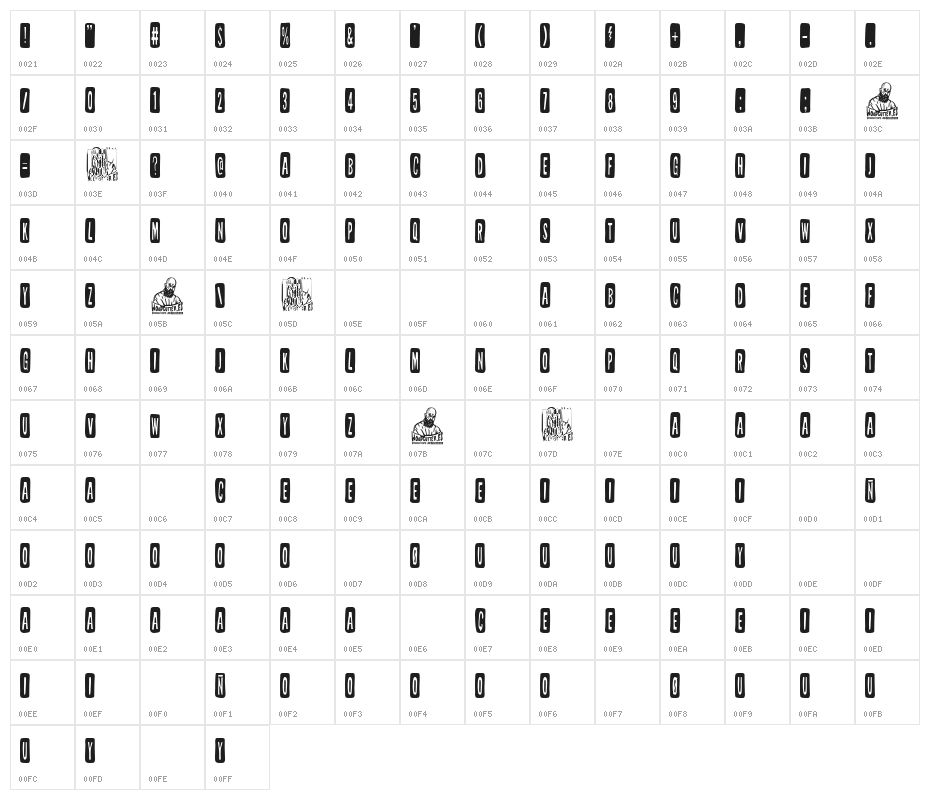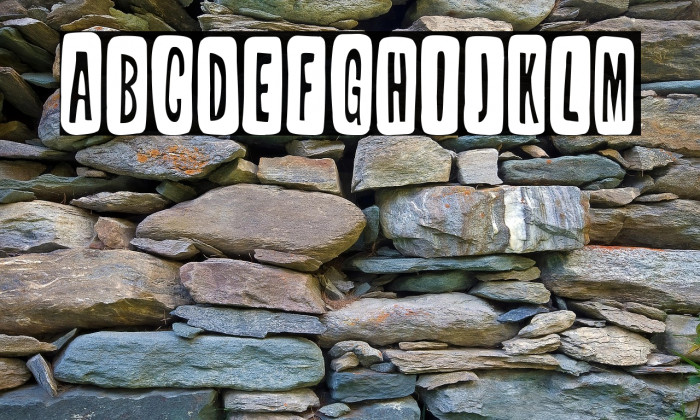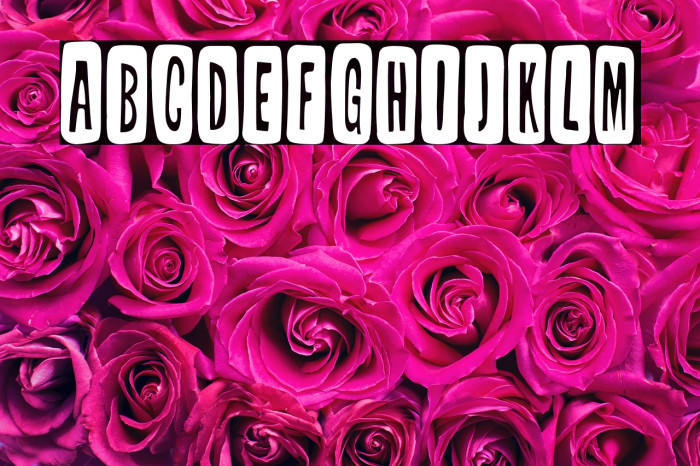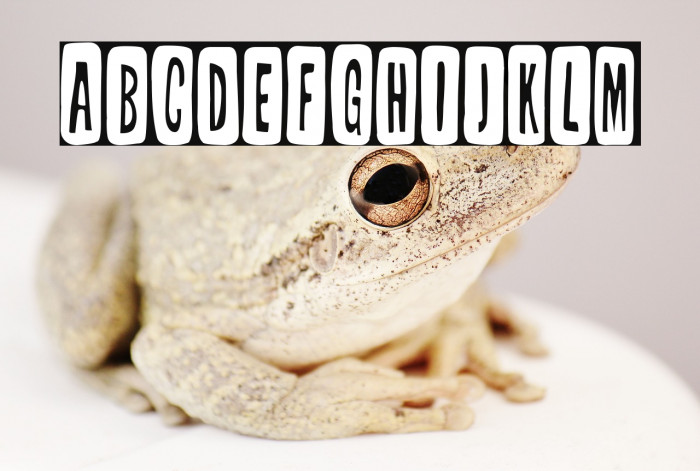
Tabique Nasal Font
| Gesamtstil | Playful, Quirky, Dynamic |
| Anwendungsfall | Headlines, Posters, Branding |
| Vorgeschlagene Projekte | Ideal for children's books, playful branding, posters, and creative digital content. |